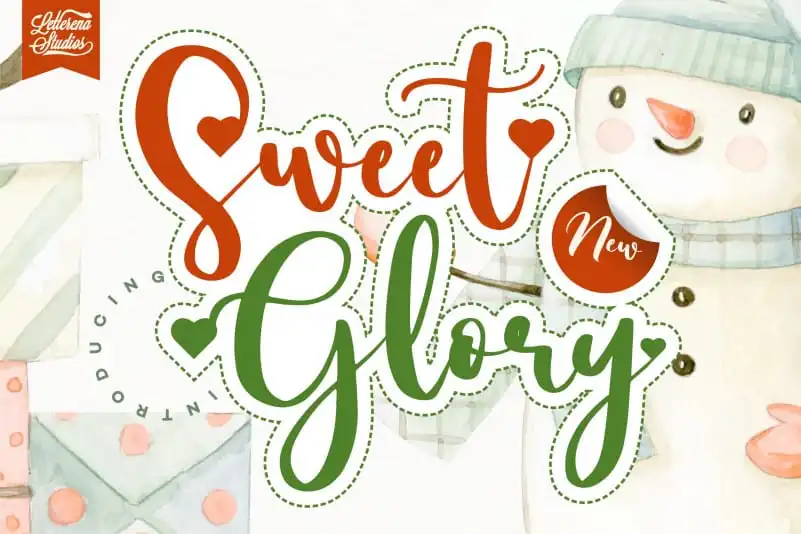
Sweet Glory Script Font – Download Grátis
A Sweet Glory Script Font é uma elegante letra escrita a mão que transmite frescor e luxo com igualdade. Ideal para cartas de aniversário, festivais ou qualquer projeto de decoração que necessite de um toque romântico. Essa fonte inclui todos os sinais e contornos (swashes) em seu conjunto de caracteres, devido à sua codificação PUA. Esta característica facilita o uso e a experiência de escrever textos com este belo estilo. Com a Sweet Glory Script Font, você pode criar projetos personalizados que transmitem sentimentos especiais em um formato encantador e moderno. Ideal para decorações de casamentos, festas infantis ou qualquer ocasião especial onde desejará expressar suas emoções através da escrita.